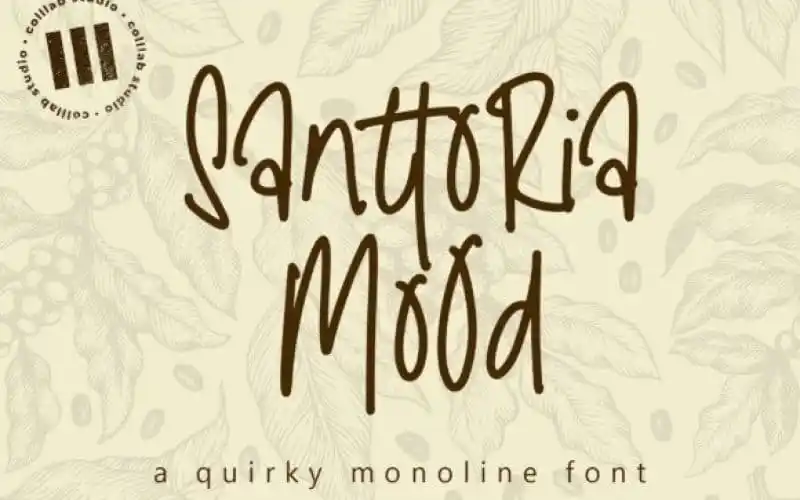
Santtoria Mood Handwritten Font – Download Grátis
A Santtoria Mood Handwritten Font é uma escolha perfeita para quem busca uma fonte elegante e natural ao mesmo tempo. Esta fonte está criada no estilo de letra cursiva serifada, mas sem traços, com um aspecto simples e minimalista que se destaca em qualquer projeto de design. Se você procura algo casual e divertido, a Aurista Handwritten Sans é uma ótima alternativa — outra fonte de letra cursiva sans-serif que traz o seu toque de informalidade. Ambas as fontes são perfeitas para trabalhos como posters, banners e logotipos, adicionando um toque criativo e único a qualquer projeto. A Santtoria Mood oferece uma sensação leve e simples, ideal para textos de pequenas dimensões ou se você deseja criar um visual mais elegante em projetos maiores. Já a Aurista Handwritten Sans é perfeita para quem procura um estilo mais despojado e casual em seus designs. Essas fontes são uma excelente adição à sua coleção de recursos gráficos, fornecendo um toque criativo que enriquece qualquer projeto visual. Combinadas ou separadamente, elas trazem sofisticação com um toque de naturalidade, tornando seu trabalho único e inovador.